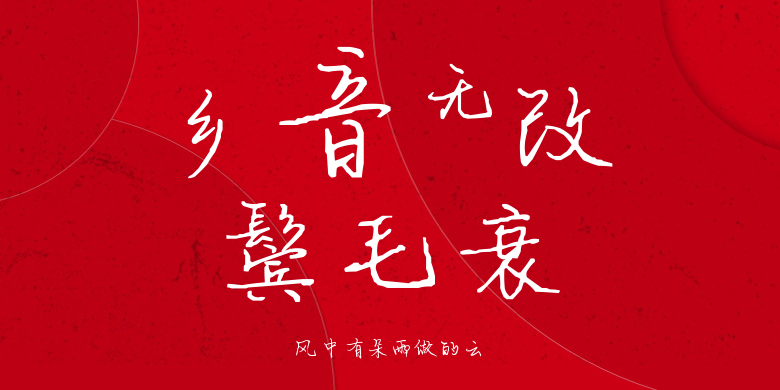
风中有朵雨做的云
风中有朵雨做的云,这款字体结构工整、笔画清晰,兼顾美观与易读性,适用于标题、正文、海报、包装、LOGO 等多种场景。字形优雅稳定,风格百搭耐看,适配日常排版与创意设计,让文字呈现更舒适、更具质感。风中有朵雨做的云一笔一画,皆是细节,以均衡的比例、流畅的线条打造舒适视觉体验,字形端正大气,风格简约现代。无论是商业设计、品牌宣传还是日常排版,都能轻松驾驭,让文字更有格调与力量。风中有朵雨做的云字体下载。